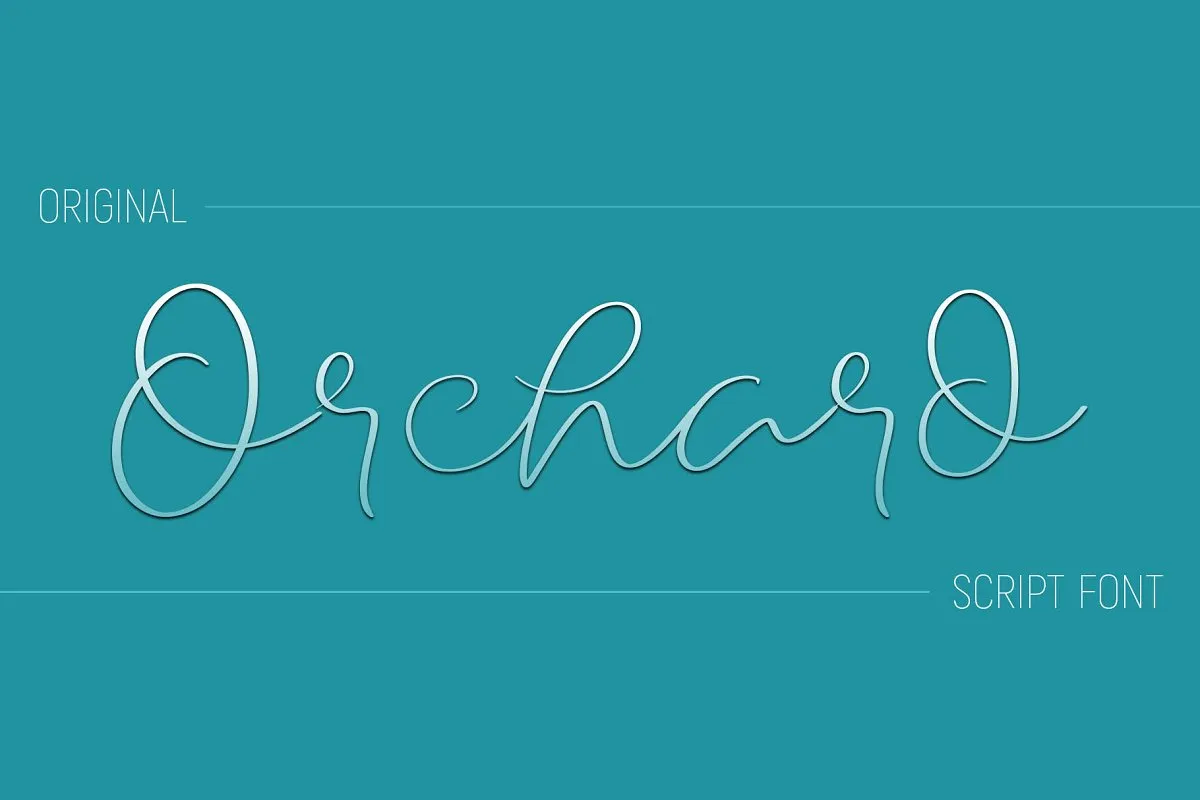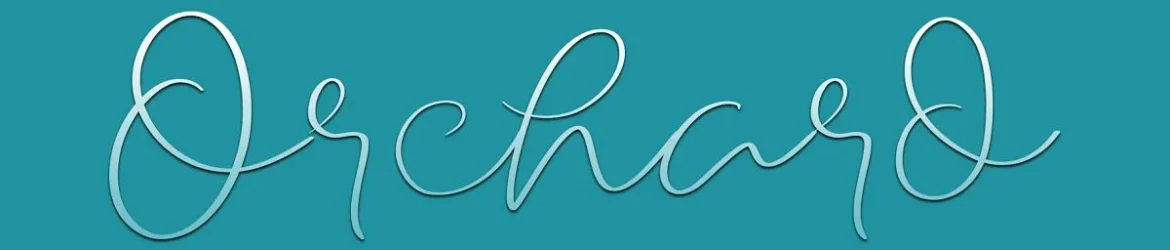
A Orchard Script Font é uma opção perfeita para os criadores que buscam dar um toque autêntico a seus projetos digitais. Esta font script original traz a sensação de escrita feita à mão, garantindo resultados impressionantes que combinam perfeitamente com o design e o conteúdo. Perfeito para quem procura manter uma mensagem aparentemente natural e delicada em seu projeto, esta fonte oferece uma textura única e realista, dando vida a designs que se parecem quase que completamente autênticos. Para aqueles que estão buscando um toque personalizado em sua identidade visual ou em elementos de logotipo ou assinatura, a Orchard Script Font é perfeitamente adequada. Suas linhas leves e detalhes naturais permitem uma aplicação versátil para diversos ambientes, seja no design editorial, moda, branding ou qualquer outro tipo de projeto que valoriza um toque delicado e autêntico em sua apresentação final. Essa fonte é a escolha perfeita para quem busca criar uma conexão direta e emotiva com seu público através da sua comunicação visual.